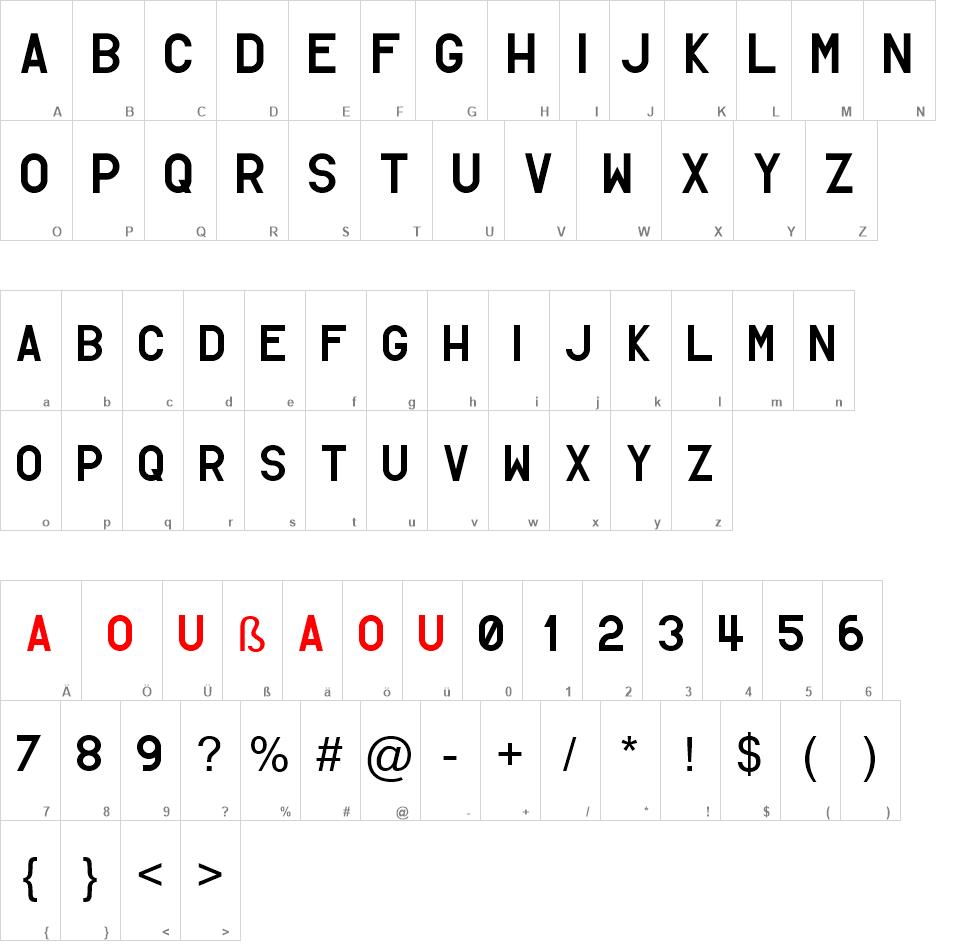
Simpleton Gothic
Simpleton Gothic font
Simpleton Gothic ist eine schrille neugroteske gotische Sans Serif. Die Schrift ist so proportioniert, dass sie genau das Gegenteil von Eleganz darstellt.